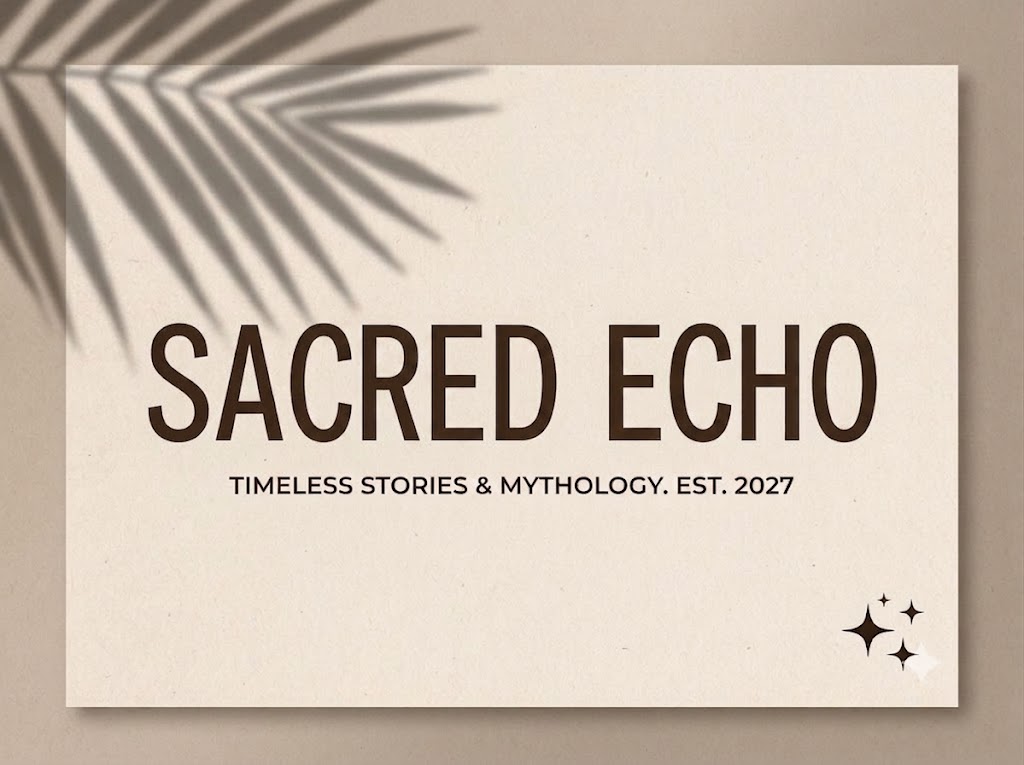
1FTV Port Credit
Trong không gian thiết kế đồ họa hiện đại, bên cạnh các dòng phông chữ hình khối hầm hố hay tối giản kĩ thuật số, những kiểu chữ display mang hơi hướng nghệ thuật cổ điển (vintage/retro) luôn có một sức hút mê hoặc riêng.
Một bộ chữ sở hữu những đường cong mềm mại, thanh mảnh và có chiều sâu sẽ giúp thổi hồn vào các tác phẩm nghệ thuật, tạo cảm giác quý phái, lãng mạn và tinh tế cho người xem.
Nếu bạn đang tìm kiếm một giải pháp typographic đầy chất thơ để làm tiêu đề phim, bìa sách, hay các ấn phẩm truyền thông cao cấp, thì font 1FTV Port Credit chính là sự lựa chọn không thể bỏ qua.
Giới thiệu về font 1FTV Port Credit
Font 1FTV Port Credit là một bộ chữ hiển thị sở hữu phong cách cổ điển, thanh lịch và mang đậm tính nghệ thuật sắp đặt.
Bộ font này đã được cải tiến và tối ưu hóa toàn diện lên phiên bản Version 3.001, đem lại sự hoàn thiện xuất sắc về cấu trúc đường nét cũng như độ ổn định cao khi phối chữ.
Nhờ cấu trúc kỹ thuật đồng bộ này, phông chữ đảm bảo khả năng hiển thị vô cùng mượt mà, sắc nét, giúp các nhà thiết kế tự tin ứng dụng trên mọi phần mềm chuyên nghiệp mà không lo lỗi răng cưa khi phóng to.
Đặc điểm nổi bật của phong cách thiết kế Port Credit
Sức hút lớn nhất của font 1FTV Port Credit đến từ kiểu dáng mảnh mai, cao ráo kết hợp cùng những đường uốn lượn vô cùng điệu nghệ và có phần phá cách nhẹ nhàng.
Khác với các dòng font all-caps (chỉ có chữ viết hoa), Port Credit hỗ trợ trọn vẹn cả hai hệ thống chữ cái viết hoa và chữ thường đồng bộ. Điều này mang lại sự linh hoạt tối đa khi sắp xếp bố cục văn bản, giúp các dòng tiêu đề trở nên tự nhiên và thoáng mắt hơn.
Điểm nhấn nghệ thuật đắt giá nằm ở cách tạo hình đầy ngẫu hứng trên các ký tự như chữ g, y, f, j với phần đuôi uốn cong nhẹ nhàng đầy kiêu sa.
Sự kết hợp tài tình giữa cấu trúc hình học đứng dáng và nét uốn mượt mà tạo nên một diện mạo vừa hoài cổ, vừa mang tinh thần lãng mạn của các thập niên trước.
Để phông chữ vận hành mượt mà trên mọi hệ điều hành và phần mềm thiết kế, phiên bản font 1FTV Port Credit đã trải qua quy trình xử lý thông số kỹ thuật vô cùng kỹ lưỡng.
Hệ thống khoảng cách chữ (kerning) và độ giãn dòng được căn chỉnh chuẩn xác, giúp các ký tự độc lạ khi đứng cạnh nhau không bị dính nét mà vẫn tạo thành một chuỗi văn bản liền mạch, hài hòa.
Bên cạnh hệ thống chữ cái hoa và thường đồng bộ, font còn tích hợp đầy đủ dãy số từ 0-9 cùng hệ thống các ký tự đặc biệt, dấu câu thông dụng (1234567890.:,;'"(!?)+-*/=).
Bản Việt hóa chuẩn chỉnh giúp các nhà sáng tạo nội dung hoàn toàn yên tâm thiết kế các văn bản tiếng Việt có dấu mà không lo gặp phải tình trạng nhảy font hay thiếu ký tự khi gõ.
Hình ảnh demo thực tế của font 1FTV Port Credit
Kích thước nhỏ (12pt – 24pt): Nhờ khoảng trống bên trong ký tự (counter) được tính toán khoa học, các nét chữ mảnh vẫn hiển thị rõ ràng, ngay ngắn và cực kỳ dễ đọc trên màn hình di động.
Kích thước lớn (36pt – 72pt): Đây là đất diễn lý tưởng nhất để font phô diễn toàn bộ sự kiêu sa, tạo hiệu ứng thị giác lãng mạn và cao cấp cho các tiêu đề chính.
Ứng dụng của font Port Credit trong thiết kế đồ họa và làm video
Sở hữu nét cá tính lãng mạn và cấu trúc hoa – thường tinh tế, font 1FTV Port Credit mở ra không gian ứng dụng rộng lớn cho các dự án truyền thông:
Thiết kế bìa sách, tạp chí và Poster nghệ thuật: Hoàn hảo cho các ấn phẩm thuộc chủ đề văn học, thơ ca, thời trang vintage, kiến trúc cổ điển hoặc các triển lãm nghệ thuật sang trọng.
Làm tiêu đề video ngắn (TikTok, Reels, Shorts): Rất thích hợp cho các video dạng chữa lành, vlog đời sống nhẹ nhàng, kể chuyện tâm sự hoặc chia sẻ các thông điệp sâu lắng, đầy chất thơ.
Ảnh thu nhỏ YouTube (Thumbnail): Đặc biệt hiệu quả với các kênh về âm nhạc acoustic, review sách, phim ảnh, chia sẻ phong cách sống tối giản hoặc nội dung lịch sử, văn hóa.
Nhận diện thương hiệu và bao bì phong cách luxury: Phù hợp làm logo dạng chữ, biểu ngữ quảng cáo hoặc nhãn mác cho các tiệm hoa nghệ thuật, thương hiệu mỹ phẩm hữu cơ, tiệm bánh ngọt hay các quán cà phê lãng mạn.